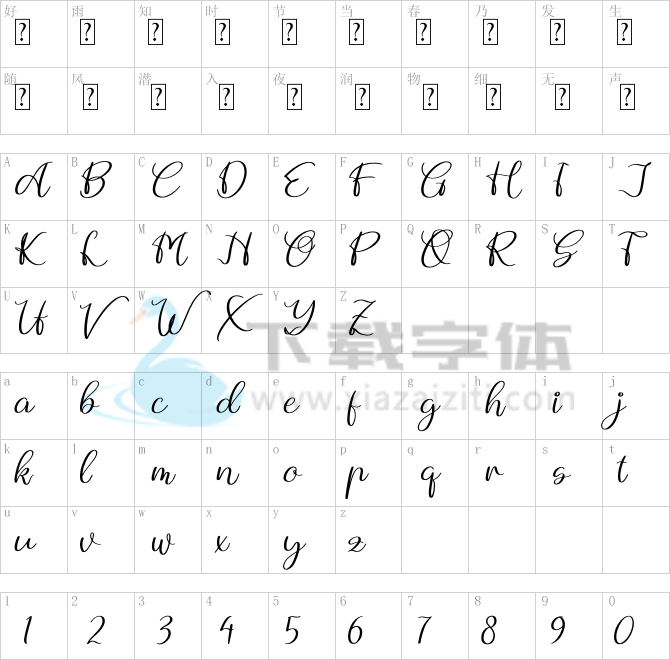
Andytta Selya.ttf字体下载
Andytta Selya.ttf字体下载,这款字体结构工整、笔画清晰,兼顾美观与易读性,适用于标题、正文、海报、包装、LOGO 等多种场景。字形优雅稳定,风格百搭耐看,适配日常排版与创意设计,让文字呈现更舒适、更具质感。Andytta Selya.ttf字体下载一笔一画,皆是细节,以均衡的比例、流畅的线条打造舒适视觉体验,字形端正大气,风格简约现代。无论是商业设计、品牌宣传还是日常排版,都能轻松驾驭,让文字更有格调与力量。Andytta Selya.ttf字体下载字体下载。